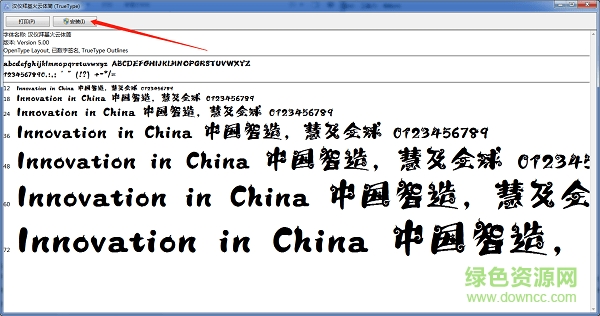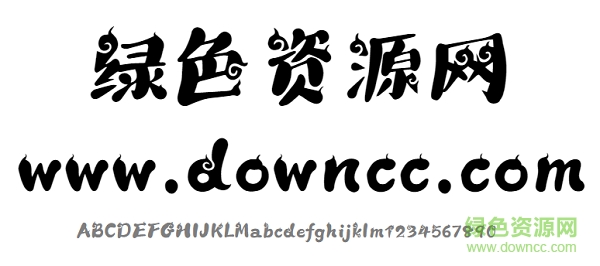
漢儀拜基火云體w
漢儀拜基火云體,超有個(gè)性的一款字體,是漢儀字體最新發(fā)布的藝術(shù)字體,整個(gè)字體就像是一簇火苗,用戶各大作品排版過(guò)程中非常的有個(gè)性,還可以作為標(biāo)示性字體讓文章內(nèi)容變的更加的醒目,需要的用戶就來(lái)綠色資源網(wǎng)下載吧!
漢儀拜基火云體w簡(jiǎn)介:
漢儀拜基火云體簡(jiǎn),自帶火焰特效的字體,全新的設(shè)計(jì)帶你領(lǐng)略全新的字體內(nèi)容,超強(qiáng)設(shè)計(jì)感,筆鋒奇特,讓字體帶你一起發(fā)現(xiàn)更多的不同!